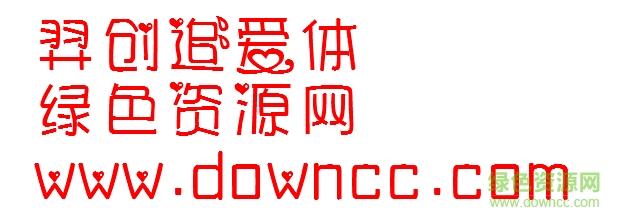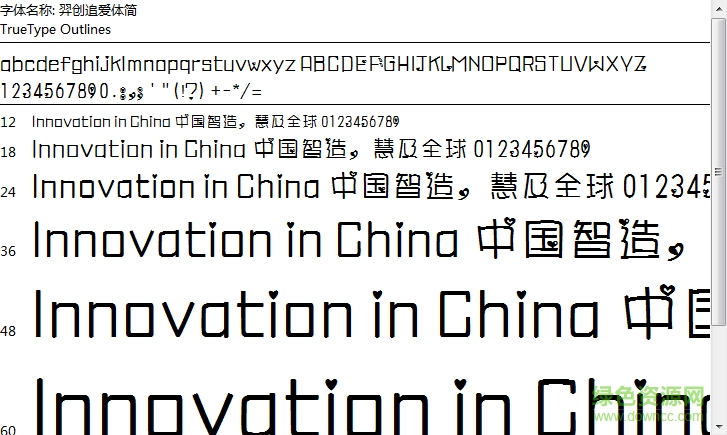
羿創(chuàng)追愛體是一款有著心形圖案的浪漫藝術(shù)字體,讓最甜美的氣息跳躍在字里行間,滿滿的都是愛,連標(biāo)點符號都生動活潑起來,喜歡的朋友千萬不要錯過哦,安裝在手機(jī)上也是很贊的!
這款手機(jī)中文字體以pop字體為原形,在筆畫間嵌入有趣的卡通心形圖形,充滿了濃濃的愛意,真是一款充滿浪漫氣息的字體,非常適合喜歡浪漫的朋友在手機(jī)上安裝使用!